タイププロジェクト、TPスカイを加えフィットフォントサービスを拡張
ウエイト、字幅、コントラストの調整に加えて、漢字、仮名、欧文の組替えも可能新たにプロダクションタイプとタイポテークの欧文フォントを追加
タイププロジェクト株式会社(東京都練馬区 代表取締役社長 鈴木 功、以下タイププロジェクト)は、本日、フィットフォントサービスを拡張し、ウエイトや字幅、コントラストを調整することが可能な「TPスカイフィットフォント」の提供を発表いたしました。また、サービス画面を刷新し、ウエイトや字幅、コントラストの調整に加えて、漢字、仮名、欧文の組替えも実現しています。
フィットフォントは、画面上のスライドバーでウエイトや字幅を調整することで、モニタのサイズやディスプレイの解像度、広告やカタログなど使用状況に応じて最適なフォントをお選びいただけるサービスです。独自開発技術により、ウエイトやコントラスト、字幅を変更した場合でも、字画の比率が適正で常にバランスの取れた状態を保ち、ダイナミックに変化しながらもデザインの一貫性と品質を保持することを実現しています。
タイププロジェクトでは、企業のメッセージを伝えるための手段としてフォントによるブランディングを提案しています。フィットフォント技術を用いて、AXIS FontやTP明朝、TPスカイのウエイトや字幅、コントラストを調節することで最適な組合せを提供します。また、欧文部を他社欧文と組替えるほか、オリジナルのひらがなやカタカナを開発するなど、世界有数のグローバル企業にコーポレートフォントを提供しています。
タイププロジェクトの鈴木功は、「フィットフォントを基盤としたコーポレートフォント提供の機会が増えていることをとても嬉しく思っています。コーポレートフォントは、企業の声に相当するものだと考えています。自社の声にふさわしいフォントを用いることで、企業のアイデンティティを表現できるとともに、長期的かつ広汎に活用することでコストの削減にもつながります。今後も、国内外の欧文書体メーカーと協業することで、フィットフォントの導入が広がることを期待しています」と述べています。
サービスの拡張
今回、フィットフォントに対応するTPスカイは、ウエイト・字幅・コントラストの3つの軸を持つ初めての日本語フォントです。TPスカイフィットフォントでは、26段階のコントラストと34段階のウエイト、16段階の字幅で、14,144のバリエーションを用意しています。UIメニューからデジタルサイネージまでの幅広い用途や、画面のサイズや使用目的に応じて最適フォントをお選びいただけます。
さらに、今回リニューアルしたフィットフォントサービスのプルダウンメニューでは、異なるフォントの漢字・仮名・欧文を組替えてご確認いただけます。
欧文フォントでは、Commercial Type(コマーシャルタイプ、米国 ニューヨーク)の欧文書体を追加するとともに、新たにProduction Type(プロダクションタイプ、フランス パリ)とTypotheque(タイポテーク、オランダ ハーグ)の書体をリストに加えました。
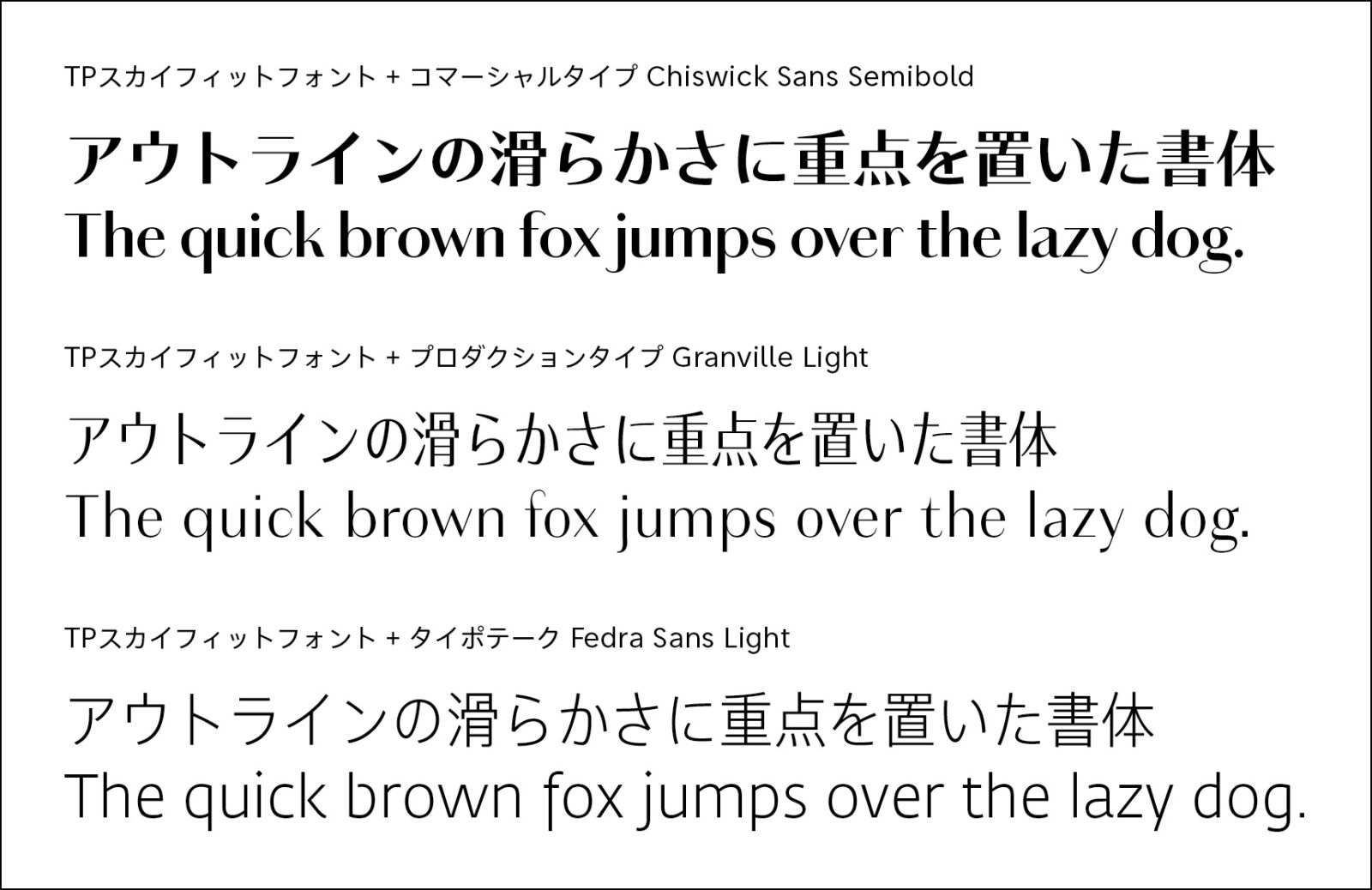
フィットフォント導入例
フランスの伝統的な自動車メーカーであるAlpine (アルピーヌ)には、プロダクションタイプが開発したAlpine Ascensionに合わせてAXIS Fontのウエイトを調整した「Alpine AXIS」を提供しました。
株式会社デンソーへコーポレトフォントフォントとして提供した「DENSO TP 2017」と「DENSO SansTP 2017」では、Kontrapunkt(コントラプンクト、デンマーク コペンハーゲン)が開発した欧文フォントに合わせてAXIS Font のウエイトを調整し、欧文書体の組替えを行いました。
また、さくらインターネット株式会社に提供した、TPスカイのカスタマイズ版の「Haru TP」では、日本デザインセンターが制作した主要な欧文と数字をTPスカイと組合せるとともに、仮名7文字のデザインをさくらインターネットのロゴイメージに合わせて変更して提供しています。